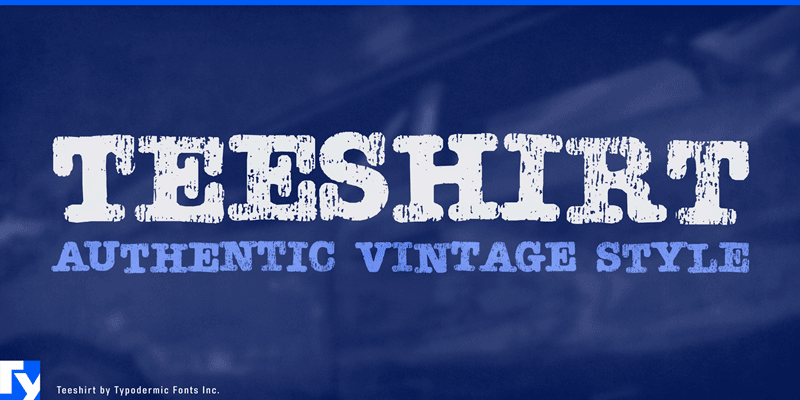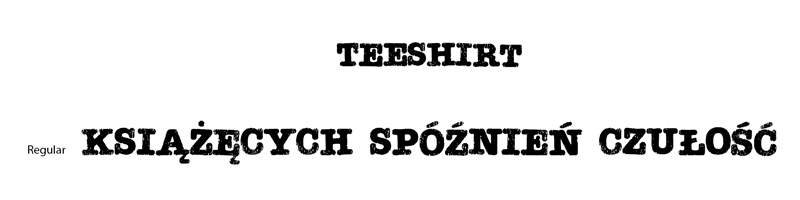
Font Teeshirt
Zakupiliśmy ozdobny font Teeshirt. Został zaprojektowany w 2008 roku przez mieszkającego w Japonii Raya Larabiego. Litery mają postać podniszczonej i odklejającej się farby, charakterystycznej dla nadruków na koszulkach z lat dziewięćdziesiątych ubiegłego wieku.